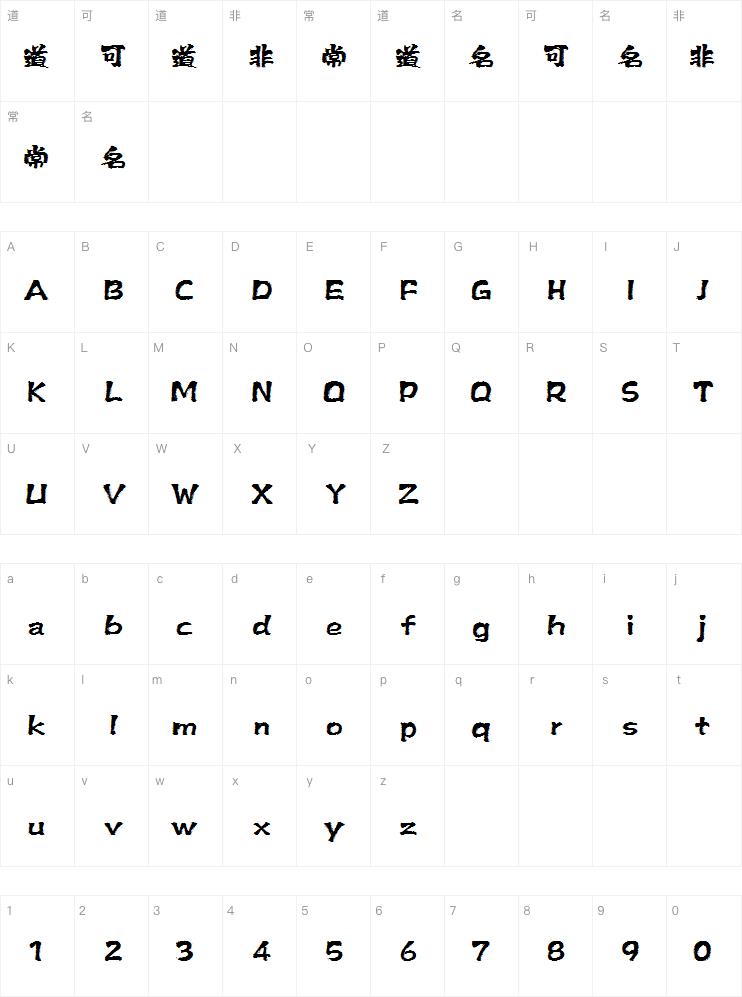
上首大圣体
上首大圣
上首大圣体,立足对中国传统书法艺术的敬畏与创新探索,融合现代字体设计的规范性与实用性,打造出兼具艺术感染力与视觉识别性的独特字体。笔画粗细变化自然灵动,起笔、收笔处保留书法 “提按顿挫” 的韵律感 —— 枯笔的涩意、顿笔的厚重等细节被巧妙还原,传递出书法艺术特有的生动质感。在遵循汉字传统间架结构的前提下,通过笔势的张扬与凝练,营造出大气磅礴、庄严肃穆的视觉张力。融入 “大圣” 所象征的豪迈刚健、充满力量感的精神内核,笔画间透着果敢与劲挺。适用于搭配标志、广告标语、商业广告等高端属性。
上首大圣体